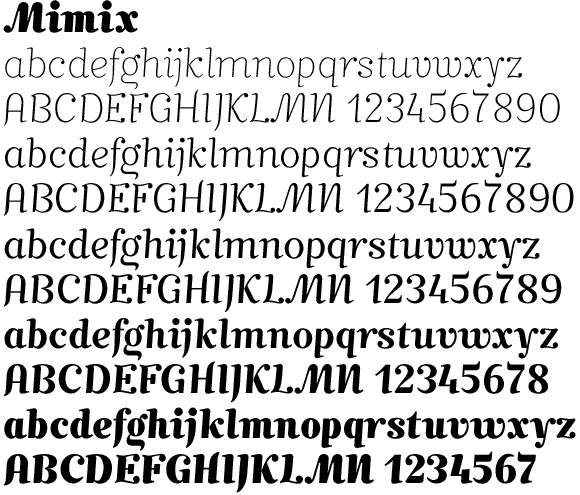
Mimix, Schrift mit Charme
Mimix ist speziell entworfen für Comicfans und alle Typografen mit Freude an Spiel und Spass. Sie verkörpert Spontanität und Lebensfreude.
Wo sie eingesetzt wird, entsteht Leben. Die Zeichen reihen sich in eine Zeile, ein Gesicht blickt aus dem Blatt entgegen. Grosse Ohren umranden den ovalen Kopf. Eine Maus trollt ohne Hast, aber dynamisch und modern über die Zeilen. Die Eleganz einer klassizistischen Schrift kombiniert Mimix gekonnt mit der Spontaneität einer lockeren Handschrift. Die Maus zeigt ihren vielseitigen Charakter in ihrem breiten Anwendungsbereich. Sie spielt ohne Übertreibung, bleibt dabei immer fein und elegant. Das ruhige Schriftbild und die gute Lesbarkeit verdankt sie ihrer moderaten Schriftlage.
Gut ausgebaut, umfasst Mimix zehn Schnitte von Ultramager bis Extrafett. Unkonventionell auch bei Ligaturen, mit Sonderzeichen für osteuropäische Sprachen, mit Versal-, Mediäval- und Bruchziffern gehört Mimix in jeden typografischen Spielkasten.
Erkläre den Bleiwüsten den Kampf – mit Mimix, die mit Charme.
Mimix ist speziell entworfen für Comicfans
Das wäre mir zugegebenermaßen nicht aufgefallen.